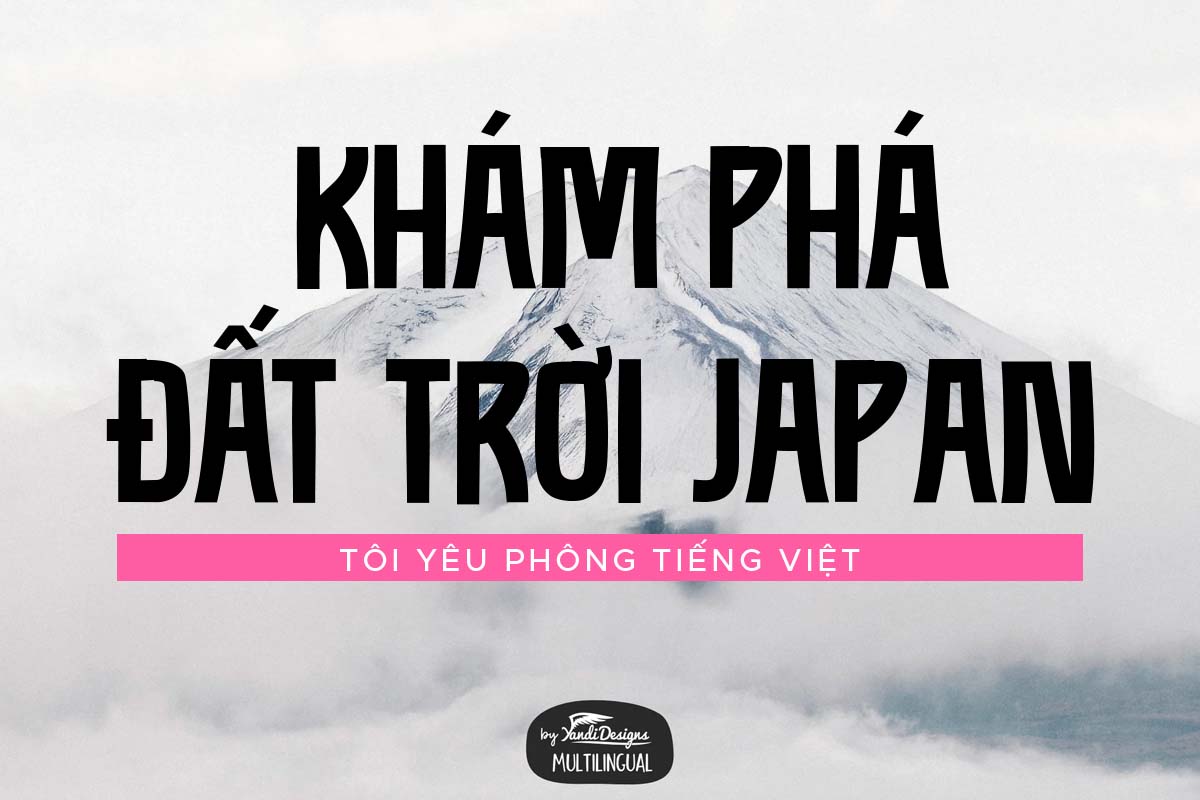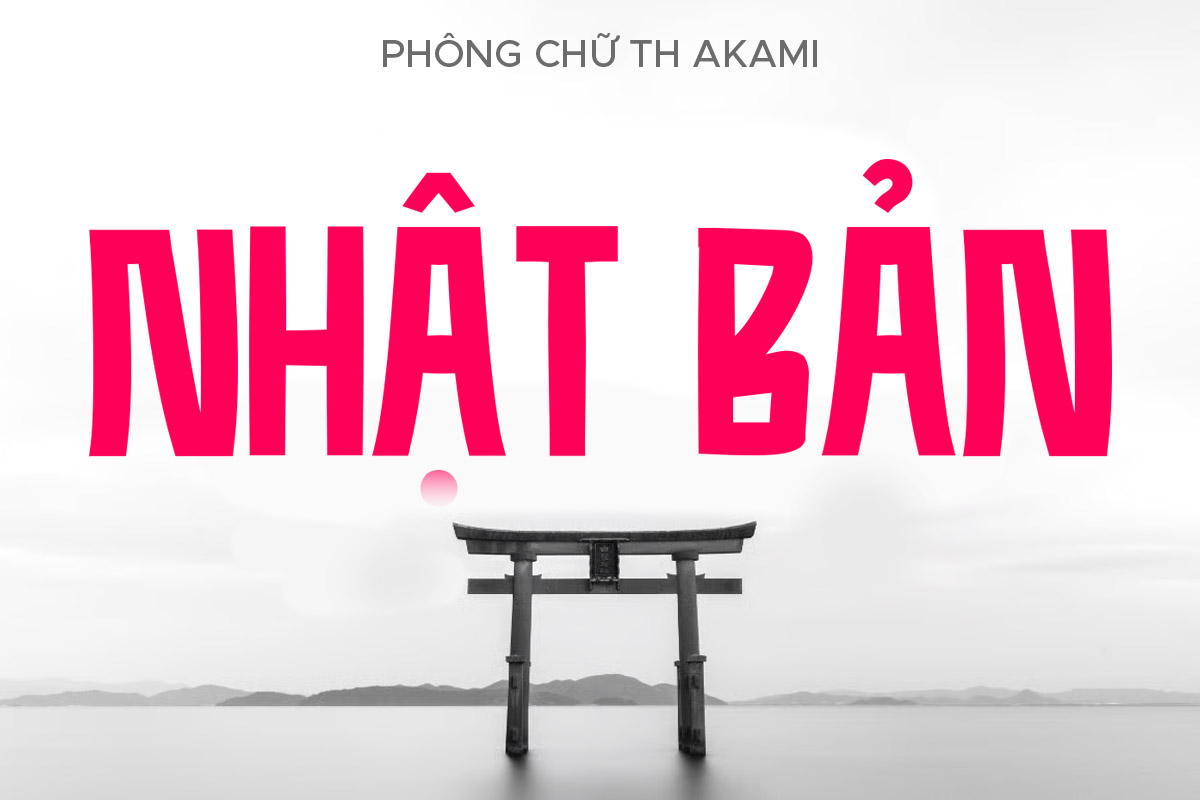
Phông chữ nhật bản Việt hóa TH AKAMI
Tác giả Yandi designs
Akami là một font chữ mang đậm tinh thần Á Đông hiện đại, được thiết kế bởi Yandi – nhà thiết kế font nổi tiếng với phong cách tối giản nhưng giàu cá tính. Lấy cảm hứng từ thẩm mỹ Nhật Bản, Akami gây ấn tượng mạnh ngay từ cái nhìn đầu tiên bởi cấu trúc chữ gọn gàng, nét thẳng dứt khoát, hạn chế tối đa các chi tiết thừa. Chính sự tiết chế này tạo nên cảm giác cân bằng, tinh tế và rất phù hợp với xu hướng thiết kế đương đại, nơi tính rõ ràng và cảm xúc thị giác được đặt lên hàng đầu. Đây cũng là lý do Akami thường được nhắc đến như một font chữ Nhật Bản hiện đại, dù vẫn giữ được sự linh hoạt khi ứng dụng trong nhiều bối cảnh khác nhau.
Về mặt kiểu dáng, Akami thuộc nhóm font display sans-serif, có độ dày nét ổn định, hình khối rõ ràng và khoảng cách chữ được tính toán hợp lý. Các ký tự mang hơi hướng hình học, gợi liên tưởng đến bảng hiệu, poster và các ấn phẩm thị giác của Nhật Bản, nơi sự tối giản luôn song hành cùng tính biểu đạt mạnh mẽ. Font cho cảm giác chắc chắn, hiện đại nhưng không khô cứng, nhờ vào cách xử lý bo góc vừa phải và tỷ lệ chữ hài hòa. Nhờ đó, Akami đặc biệt phù hợp cho tiêu đề, logo, banner, thiết kế thương hiệu hoặc các sản phẩm sáng tạo cần tạo điểm nhấn thị giác rõ ràng.
Nhằm phục vụ tốt hơn cho cộng đồng thiết kế trong nước, font chữ Akami đã được Team TH Việt hóa hoàn chỉnh và ra mắt với tên gọi TH Akami. Quá trình Việt hóa không chỉ đơn thuần là bổ sung dấu tiếng Việt, mà còn là sự tinh chỉnh tỉ mỉ để các ký tự có dấu vẫn giữ được tinh thần thiết kế ban đầu. Nhờ đó, TH Akami trở thành một font chữ Việt hóa chất lượng cao, đảm bảo tính thẩm mỹ, dễ đọc và đồng bộ khi sử dụng trong các ấn phẩm tiếng Việt.
Với sự kết hợp giữa nguồn gốc thiết kế quốc tế và quá trình Việt hóa chuyên sâu, TH Akami mang đến cho designer một lựa chọn vừa mang hơi thở Nhật Bản hiện đại, vừa phù hợp với nhu cầu sử dụng thực tế tại Việt Nam. Đây là font chữ lý tưởng cho những ai đang tìm kiếm một font chữ Nhật Bản phong cách tối giản, đồng thời cần một font chữ Việt hóa chỉn chu để ứng dụng linh hoạt trong branding, truyền thông và các dự án sáng tạo dài hạn.